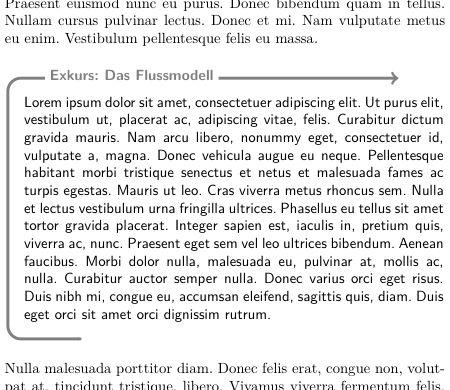
Darstellung/Hervorhebung von Exkursionen vom Haupttext/-thema
ich erstelle grade die Abbildungen für ein Physikbuch und habe mich bei der Gelegenheit auch mal der Frage angenommen, wie man die Exkurse vom Haupttext absetzten könnte. Der Auoter verwendet diese um interessante (aber nebensächliche) Aspekte und weiterführende Erklärungen unterzubrigen – soweit ich das überblicke.
Seine Lösung war nun ein fetter schwarzer Balken oberhalb und unterhalb. Das das nicht toll ist war schnell einzusehen und Alternativen mussten her. Mein erster Gedanke war eine schnöde graue Hinterlegung, mein zweiter war es das Wort „Exkurs“ aufzugreifen und, verstanden als kleine Umleitung weg von der Hauptstraße zu interessanten Dörfern an Nebenstrecken gelegen, durch einen Pfeil zu smybolisieren. Was dabei rausgekommen ist zeigt diese PDF und dieses Bild
Das ist bisher nur eine Skizze und dass der Pfeil noch etwas schöner gezeichnet werden muss ist klar. Aber was haltet ihr von der Idee oder fallen euch alternativen ein?
Umgesetzt wird das ganze in LaTeX und schwarz-weiß.
@Ralf: Sorry aber die Schrift hat der Verlag vorgegeben :-?
Ich würde die Linie oben stumpf und nicht als Pfeil aufhören lassen. Der Pfeil irritiert mich, weil er nach rechts zeigt, der Exkurs steht aber darunter. Außerdem würde ich die Linie statt auf die Höhe der Unterkante der Buchstaben auf deren Mittelhöhe setzen.
Ich finde gerade die Position der Überschrift bezüglich der Linie gut, da diese dadurch etwas hervorgehoben wird, und würde vermuten, dass sie sonst zu nah an den Text heranrücken würde. Aber das lässt sich wohl am besten via Experiment herausfinden.
Sorry aber die Schrift hat der Verlag vorgegeben
Und der Verlag lässt nicht mit sich reden? Da sich das Buch vermutlich an Physik-Studenten richtet: Ich kenne nicht wenige, typographisch unbewandte Physiker, die Computer Modern nicht mehr sehen können, da sie ihnen als LaTeX-Standardschrift täglich unterkommt. Mal ganz abgesehen davon, dass die Ligaturen wie Unfälle aussehen, usw.
Ich habe in der Zwischenzeit etwas rumgebastelt und konnte dem Verlag auch einen Schriftwechsel nahbringen. Nun ist die Frage, welche man da nimmt. Da mit LaTeX gearbeitet werden muss und die Schrift für den Mathematiksatz ausgebaut sein muss, ist die Auswahl nicht unbedingt groß und ich habe jetzt mal die Garamond ins Rennen gebracht.
Was haltet ihr von der Schriftwahl (auch die Kombination mit der Lato) und der veränderten Exkurs-Darstellung?
Die Garamond hat nur eine Größe, deshalb sehen hoch-/tiefgestellte Zeichen und alles andere, was kleiner gesetzt wird, dürr und zerbrechlich aus. Ich würde die Garamond deshalb nicht benutzen. Gute Formelzeichensätze sind allerdings rar. Folgende beiden haben verschiedene Größen:
Math Times
Minion Math